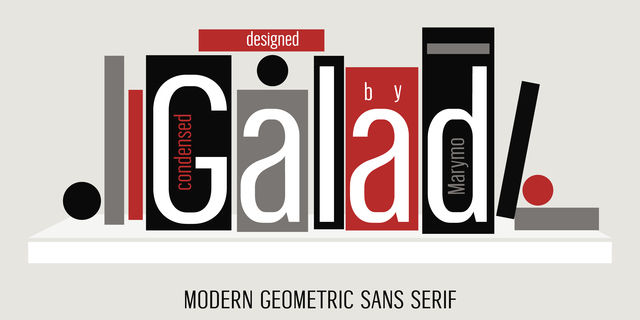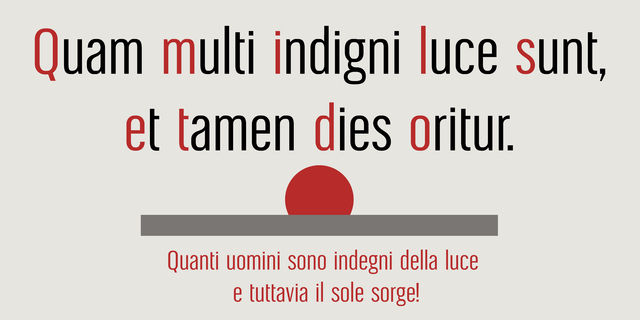
Galad – зауженный гротеск. Его разработка началась в 2017 году на курсе "Геометрический гротеск" под руководством Кирилла Ткачёва. Шрифт соединяет в себе черты, характерные герметрическим и гуманистическим шрифтам без засечек, имеет заметный контраст и полузакрытые формы. Galad предназначен для заголовков, рекламы, плакатов и небольших фрагментов текста. Шрифт разработан Марчелой Можиной и выпущен в 2018 году.
Ассоциации c семейством GaladКачества и характер:
ровный, сжатый, статичный, высокий, серьезный, взрослый, городской, устойчивый, стабильный, твердый, громкий, узкий, уверенный, качественный, точный, четкий, архитектурный, современный, стройный, деловой, строгий